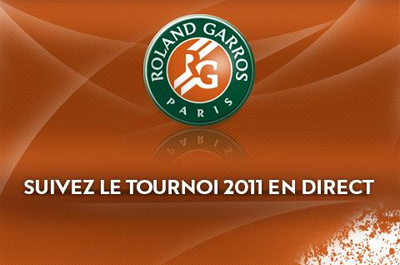
Wie heißt diese Schriftart
ich bin auf eine Schriftart gestoßen, die ich nicht ganz zuordnen kann. Es handelt sich um die Schriftart im Bild. Zuerst dachte ich Futura, aber das G in diesem Fall ist nicht rund wie bei der Futura, dann dachte ich an Neutra, aber das R hier ist auch nicht ganz richtig. Avenir ist es auch nicht, denn das N ist ja anders..
Die Metro (oder Geometric 415) geht in die Richtung, aber das ›G‹ haut nicht ganz hin. Das sieht eher nach Gotham aus ...
Vielleicht etwas selbstgebautes aus den beiden :-?
Ist es denn sicher, daß da nicht jemand mit verschiedenen Schriften gebastelt hat? Das Gesamtbild sieht ja sehr unruhig aus, was darauf hindeuten könnte.
nein ist nicht sicher. Das Bild wurde nicht zusammengebastet, ist die Wortmarke für: www-rolandgarros.fr Tennis-Turnier
Gemeint war glaube ich nicht, dass das Bild zusammengebastelt wurde, sondern dass die Wortmarke aus verschiedenen Schriften zu einem individuellen Ganzen zusammengesetzt worden sein könnte und es sich somit nicht um eine einzelne, homogene Schriftart handeln würde sondern um eine Mischung.
suche auch im Internet in Frankreich. Finde aber bis jetzt nichts. Ich finde sie schön. Bin letzer Zeit in einer geomtetrische Phase, was Schriftartena angehen...
so Designer heißt: Christophe Badani, scheint so als wäredie Schriftart speziell für das Turnier entworfen...
ich denke nicht, dass das der Name ist. RG= Roland Garros. Title=Titel und Text= Text. Aber kann sein dass ich da falsch lege
Naja ich hätte nicht einfacht RG Title/RG Text erwartet. Sondern RG Sans oder so etwas Ähnliches von einem Landsmann..